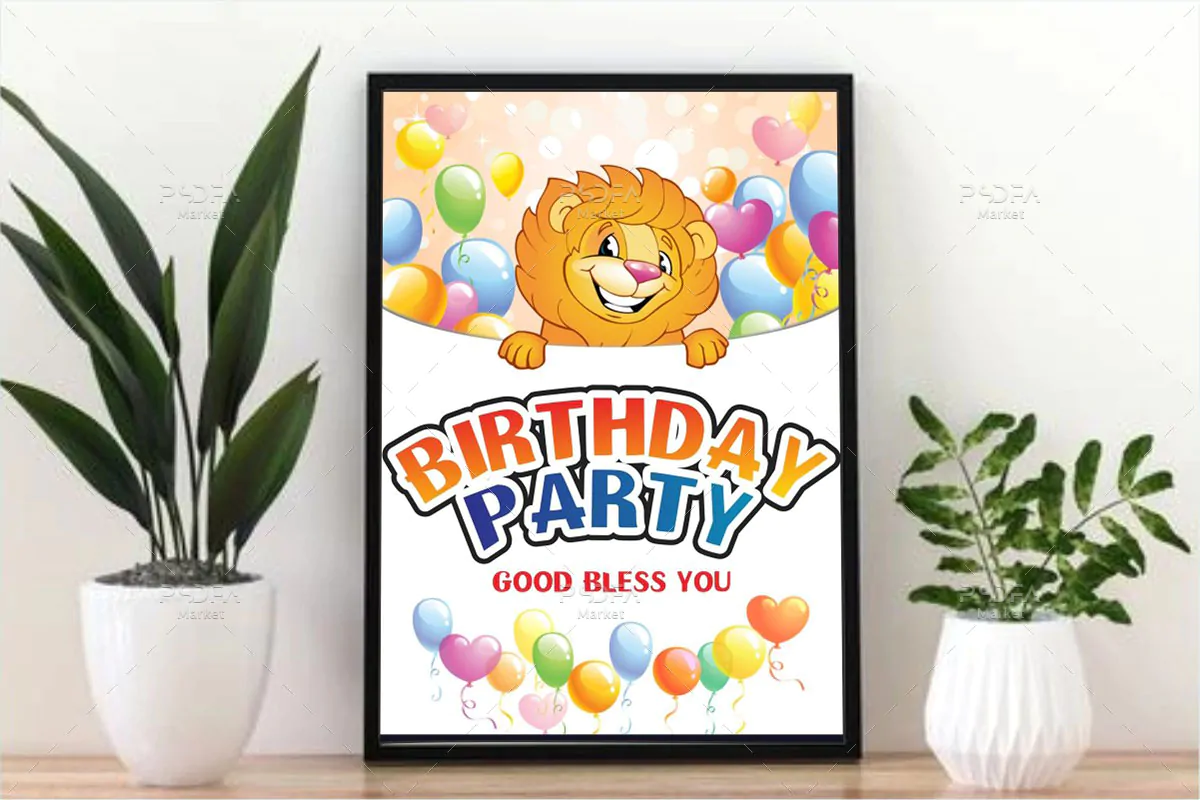
فونت مدرن کارتونی و کودکانه Happy Day
فونت مدرن کارتونی و کودکانه
فونت مدرن کارتونی و کودکانه Happy Day یک Display Font انگلیسی زیبا و شیک و خوانا است که مناسب برای استفاده در طرحهای گرافیکی مختلف میباشد. فونت Happy Day با وزن معمولی طراحی شده است که میتوانید از آن در طراحی انواع کارت تبریک، استیکر، لوازم التحریر، تقویم، بسته بندی محصولات، ظروف یکبار مصرف، پوستر و … استفاده کنید.